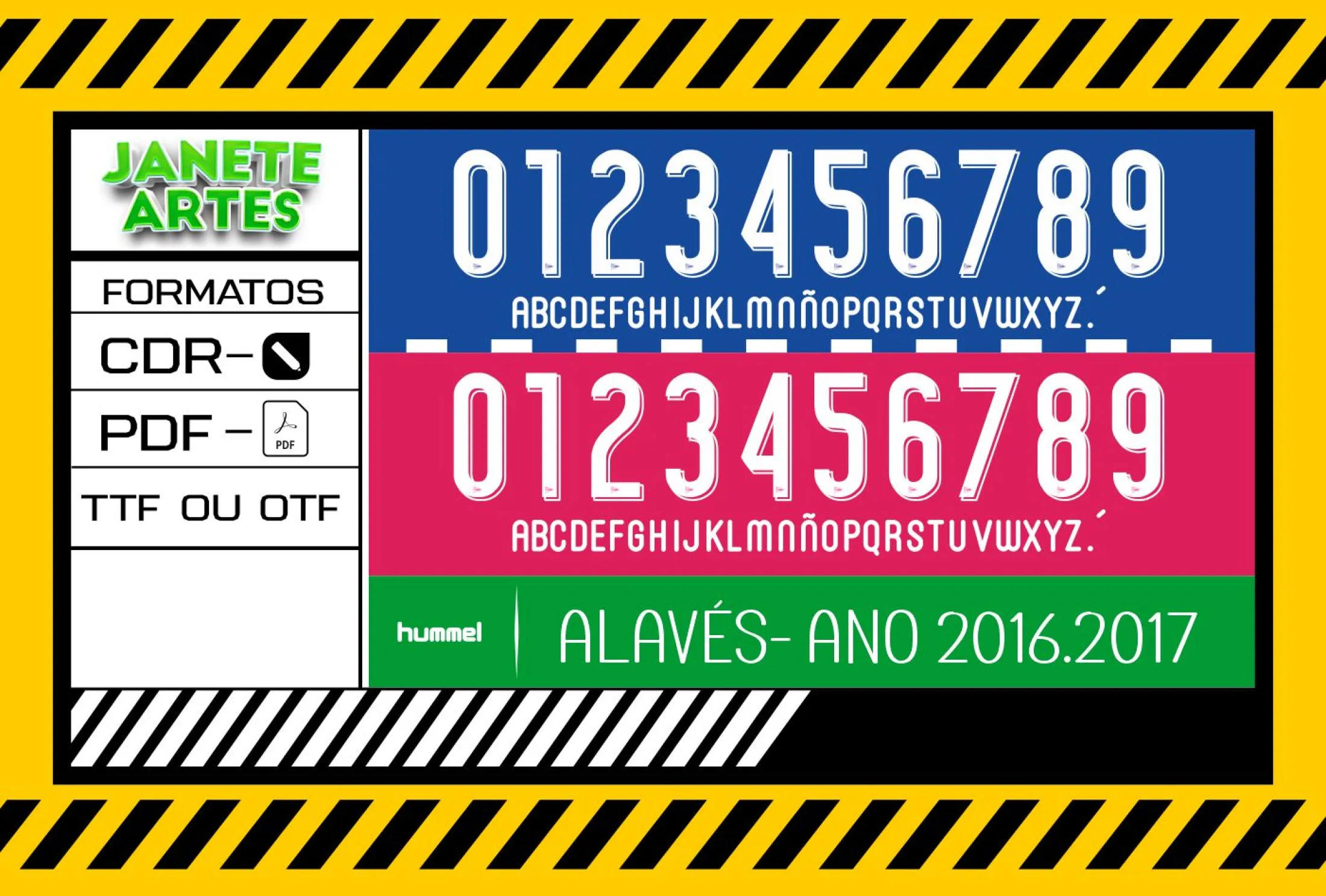
Fonte de Time Tipografia Alavés 2016 - 2017
Transforme suas camisetas com a Fonte de Time Tipografia Alavés 2016 - 2017, um arquivo digital perfeito para personalizar roupas com o estilo único do time Alavés daquela temporada icônica.
Uma paixão transformada em design
Imagine o orgulho de um torcedor do Alavés ao vestir uma camiseta personalizada com a fonte oficial do time de 2016 - 2017. Foi assim que surgiu a ideia de criar a Arte Fonte de Time Alavés 2016 2017 para Camiseta, trazendo uma conexão forte entre a torcida e o visual das camisas originais. Muitos fãs sentem falta desse estilo autêntico e agora você pode reviver essa época com um toque exclusivo na sua roupa.
O que você recebe e como usar